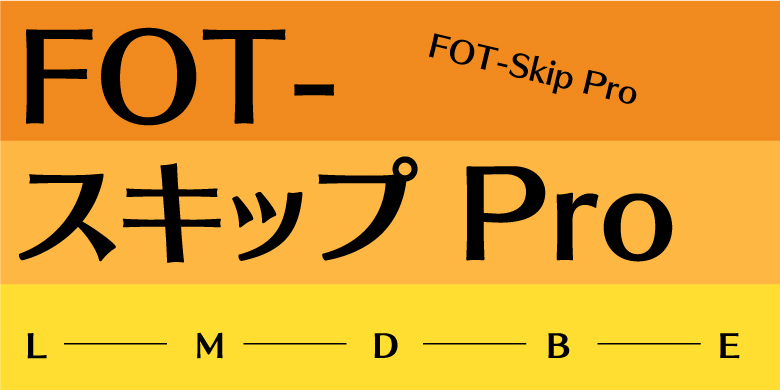
FOT-Skip Pro家族
FOT-Skip Pro家族,这款字体结构工整、笔画清晰,兼顾美观与易读性,适用于标题、正文、海报、包装、LOGO 等多种场景。字形优雅稳定,风格百搭耐看,适配日常排版与创意设计,让文字呈现更舒适、更具质感。FOT-Skip Pro家族一笔一画,皆是细节,以均衡的比例、流畅的线条打造舒适视觉体验,字形端正大气,风格简约现代。无论是商业设计、品牌宣传还是日常排版,都能轻松驾驭,让文字更有格调与力量。FOT-Skip Pro家族字体下载。
自2003年发布“Skip-B”以来,LETS会员对其系列化的需求极高,因此该字体也相应发展成5种字重的家族。这种字体在给人以严肃印象的同时,也融入了适度的时尚感,以「方形类型」(スクエアタイプ)表现出来。它是继方角黑体之后的另一种常规字体,相比黑体能表达更加《直率且温柔》的形象。